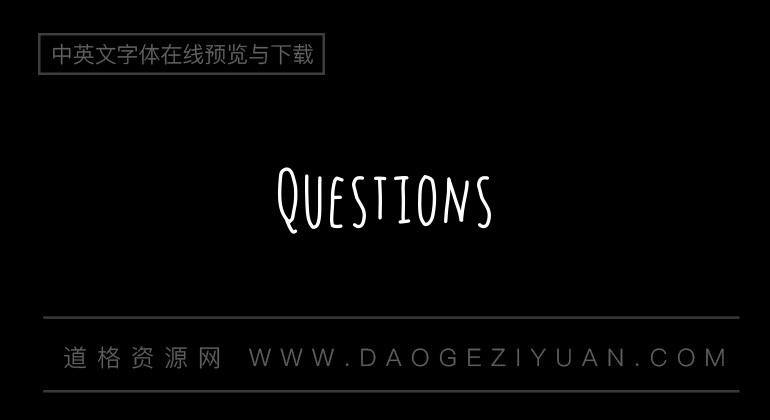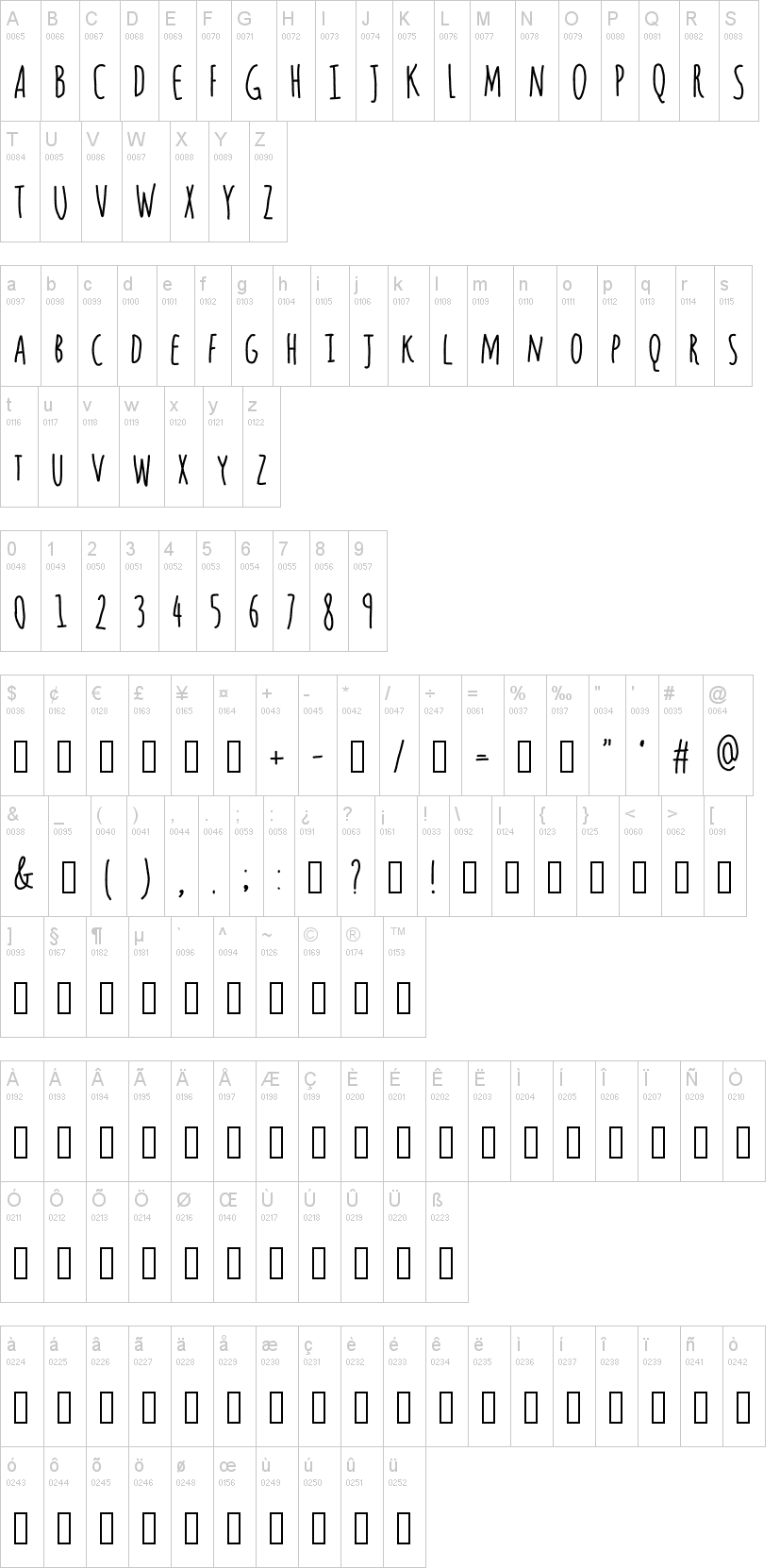
Questions 是一款简约的英文字体,由两位设计师,即Johan Kallas和Mikko Nuuttila共同设计,它是一个简单、清晰、活泼的字体,可以用于大多数文字类型。它的字体特点是简洁、大胆、活泼,它的特点是字体粗细分明,笔画流畅,字形简单,易于识别,易于理解,适合用于标题、标签等场景。内容介绍
Questions是一款非常不错的手写艺术字体,具有很好的视觉感,适合于文化类的宣传设计、商业类品牌的广告和产品包装设计以及个性化文字排版等较多场景。